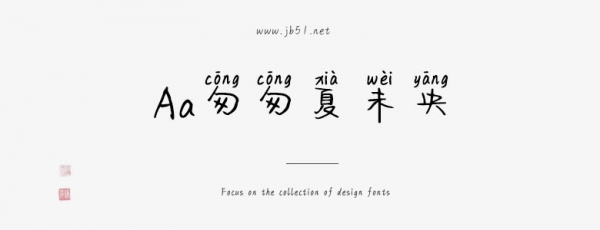
Aa匆匆夏未央是一款不錯的藝術(shù)字體,由Aa字庫出品,字體筆觸纖細(xì),書寫流暢,擁有字符數(shù)9984和字形數(shù)16806,具有很好的視覺感,適合應(yīng)用于藝術(shù)設(shè)計、平面宣傳設(shè)計、網(wǎng)頁設(shè)計,書法字帖等領(lǐng)域,需要的朋友可以前來本站下載。